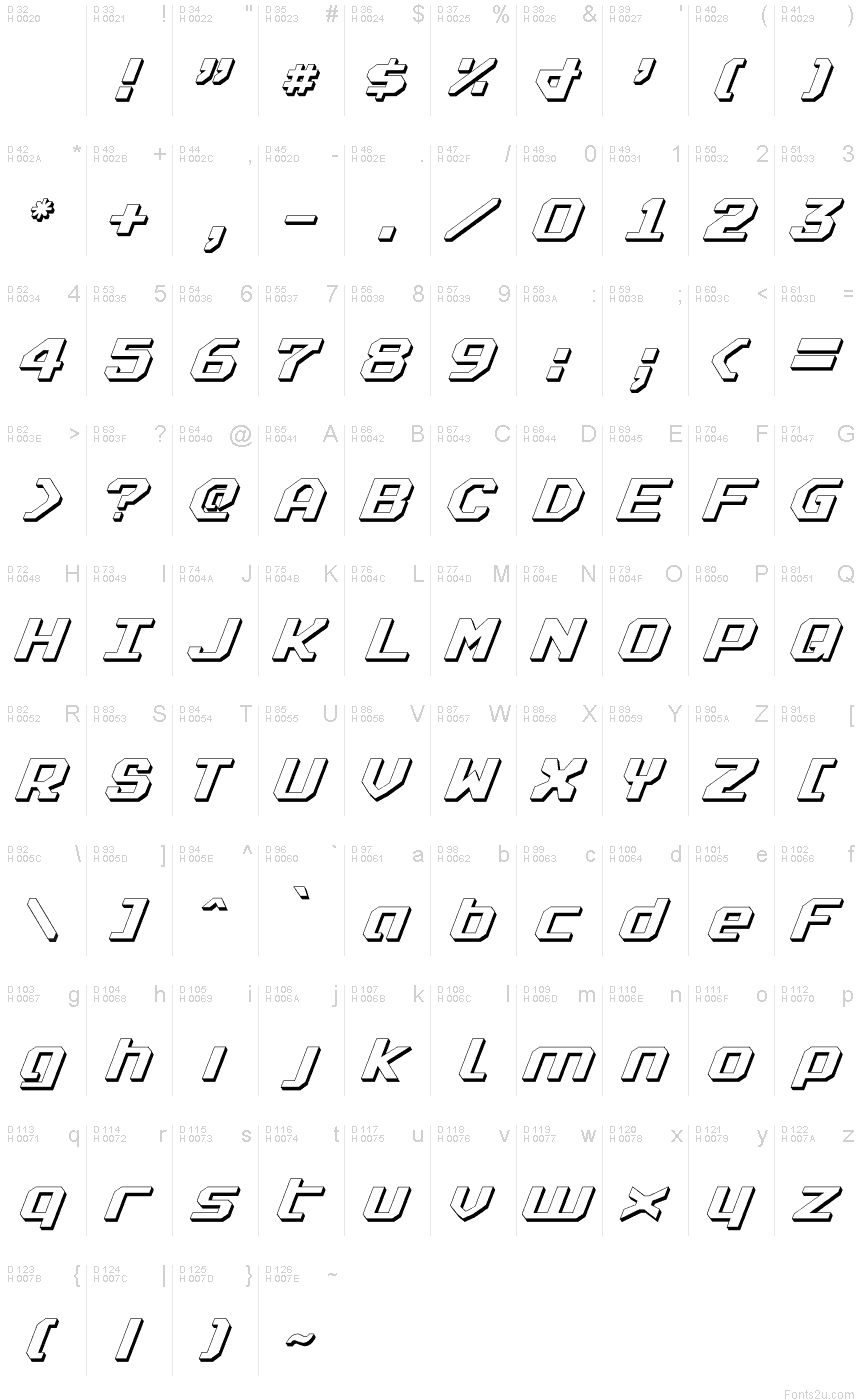
Realpolitik Shadow Italic od Iconian Fonts to nowoczesny, darmowy font 3D typu display, wyróżniający się dynamicznym, komiksowym nachyleniem i wyrazistym, przesuniętym cieniem. Litery wyglądają, jakby zostały wycięte z ciężkich bloków i pochylone do przodu; szerokie, białe wnętrza i czarne obramowania nadają całemu alfabetowi akcyjny, plakatowy charakter.
Ten darmowy font świetnie sprawdzi się w logotypach gier, opakowaniach w stylu sci-fi, ulotkach, planszach tytułowych i krótkich nagłówkach, gdzie pochylenie i cień grają główną rolę. Doskonale nadaje się również do projektowania odznak czy wyrazistych monogramów, ponieważ nałożony obrys i efekt cienia nadają nawet kilku literom wagę gotowej grafiki.